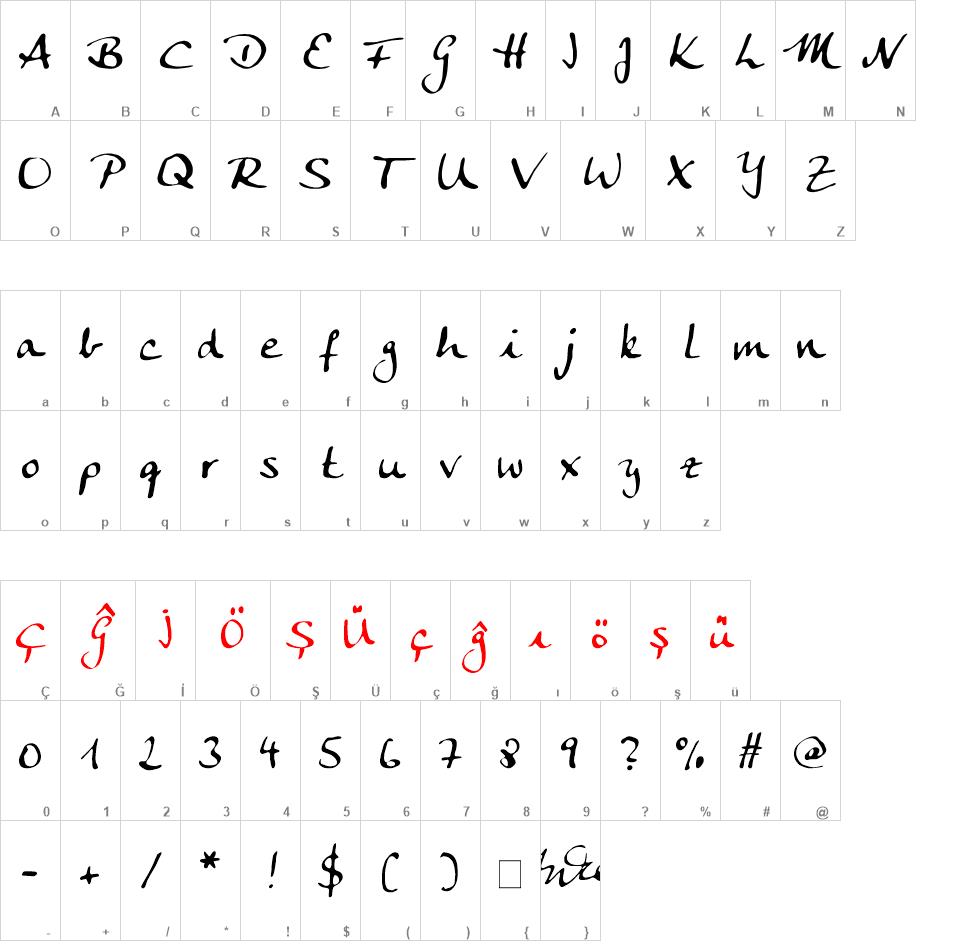
Anke Calligraphic FG
Anke Calligraphic FG font
Ursprünglich von Anke Arnold, www.anke-art.de, geschrieben, wurde diese handgeschriebene Schrift von internationalen Schriftzeichen unterstützt und von Fontgrube AH neu arrangiert sowie vertikale Anpassungen vorgenommen, wobei 100 Kernpaare hinzugefügt wurden, um ein reibungsloseres Arbeiten zu ermöglichen. Stellen Sie also sicher, dass Sie das Kerning verwenden sein. Es wird in Ihrem Textverarbeitungsprogramm oder in Ihrem DTP-Programm geöffnet. Die Schrift versucht, eine komfortable Handschrift mit einer kalligrafischen Taschenlampe nachzuahmen, ohne die OpenType-Funktionen zu unterstützen. Es ist für den täglichen Gebrauch bestimmt, kann jedoch im professionellen Kontext kostenfrei verwendet werden.